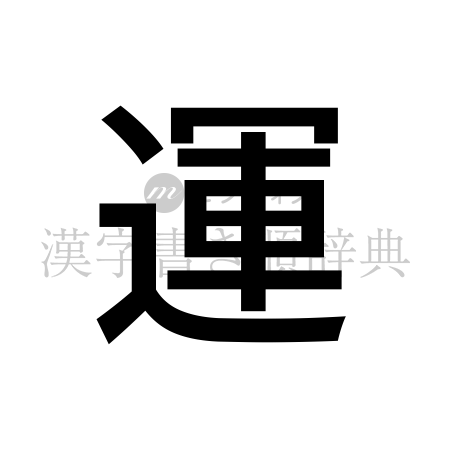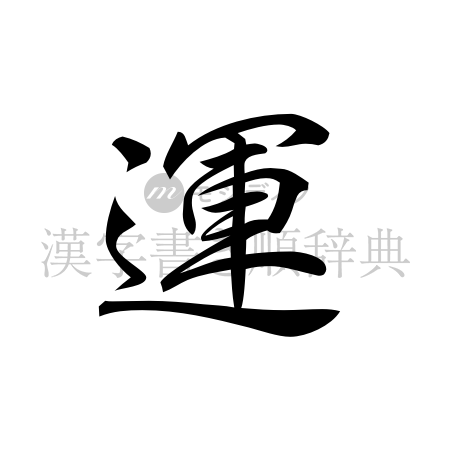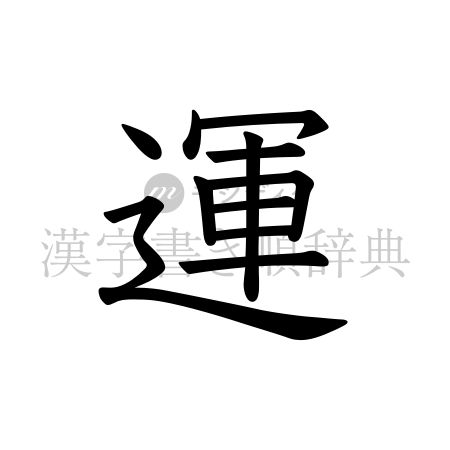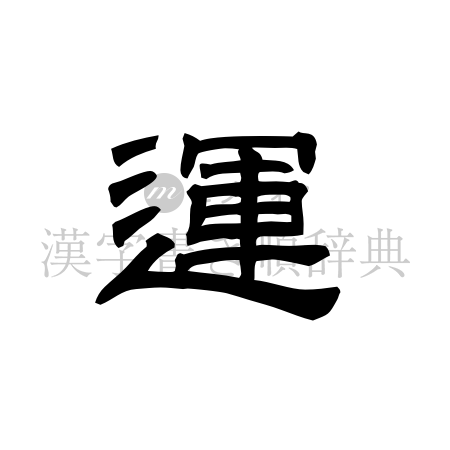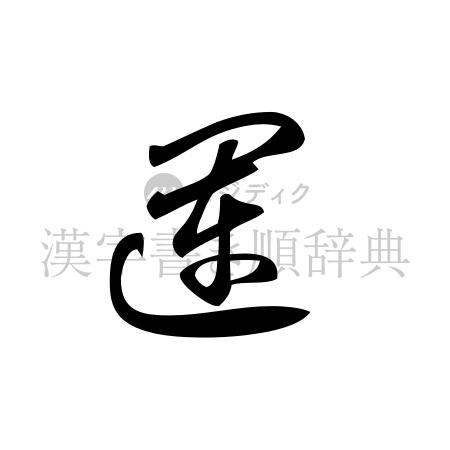
「運」の書体
• 運の書体「ゴシック体」のイメージ
• 運の書体「明朝体」のイメージ
• 運の書体「教科書体」のイメージ
• 運の書体「楷書体」のイメージ
• 運の書体「行書体」のイメージ
• 運の書体「草書体」のイメージ
• 運の書体「隷書体」のイメージ
• 運の書体「篆書体」のイメージ
「運」の意味
• 物事を動かすこと。
• 動き回ること。
• 運搬すること。
• 巡り合わせ。
• 運命。
• 幸運や不運。
• 機会。
• 運動。
• 運営。
「運」の意味の英訳
漢字は1文字で多様な意味を持ちますが、「運」を英語で表す場合、一般的には carry, luck, destiny, fate, lot, transport, progress, advance などがあります。
「運」の成り立ち・由来
構造 意符辵(進む・動く)+音符軍(うん)
形声文字です。進む・動く意を表す「辵(しんにょう)」を意符とし、「軍」を音符として組み合わせて成り立ちました。「軍」は音を示すとともに、戦車をぐるりと連ねてめぐらす意を含むとされ、車をめぐらせて物を動かす、めぐり動くという意味につながります。ここから「はこぶ」「めぐる」「動かす」、さらに転じて時のめぐり合わせを表す「運命」「運勢」の意へと広がりました。旧字体では二点のしんにょうで書かれ、のちに一点の「運」に整えられて現在の字形となっています。
「運」を含む熟語・単語とその意味
運送 - うんそう
品物を運ぶこと。運搬。
運搬 - うんぱん
人や物を運び移すこと。
運輸 - うんゆ
旅客・貨物を運ぶこと。
「運」の構成部品
「運」はにょうの構成として「軍(グン)」、にょうとして「辶(しんにょう)」を組み合わせた漢字です。
「運」の筆画・ストローク構成
• CJK STROKE HG
• CJK STROKE HZZP
「運」の国語施策
「運」は名前に使える漢字です。